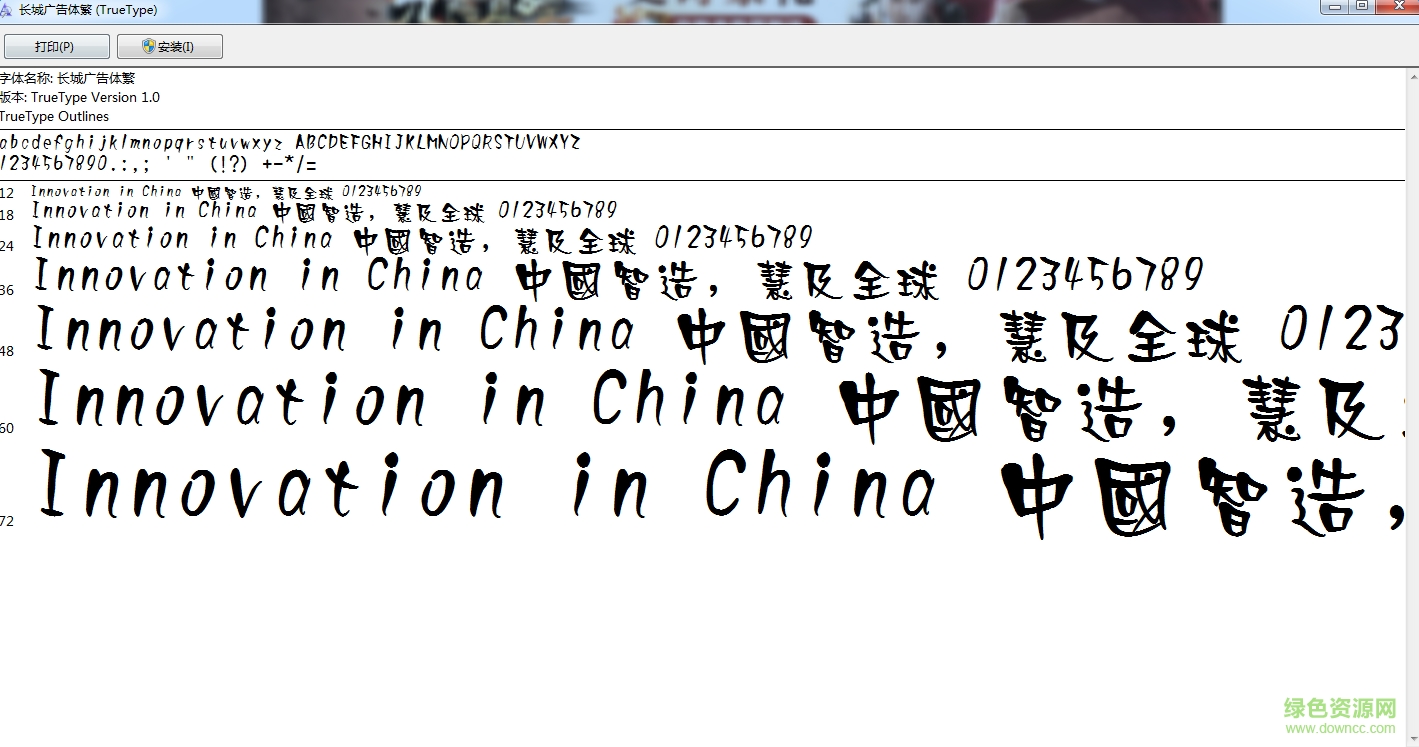
pop3eg bold t gb字體又叫長(zhǎng)城廣告體繁體字體,該字體構(gòu)思新穎,挺拔優(yōu)雅,富于韻律,視覺效果突出,常常用作廣告字體或商業(yè)字體,喜歡的小伙伴快來(lái)綠色資源網(wǎng)下載吧1
字形美觀、大方、簡(jiǎn)潔,整副字看來(lái)生動(dòng)活潑,具有流動(dòng)感,常用于美工設(shè)計(jì)方面!